Tipografía en las señales de tráfico de todo el mundo
Cuando hablamos de diseño de tipografía siempre decimos que es importante plantearse o autoplantearse un buen briefing. En este briefing uno (que no el único) de los aspectos que tenemos que tener en cuenta es donde va a ser utilizada esa tipografía, es decir su finalidad. En este aspecto hay dos "finalidades" que siempre me han producido un cierto respeto, las tipografías para texto y las destinadas a señalética.
Estas tipografias en concreto tienen que cumplir ciertos requisitos que hacen su diseño muy especial, dejando menos margen de maniobra y cuidando los pequeños detalles de una forma increíble.
Hoy nos vamos a centrar en el uso de las tipografias para señalética, y lo vamos hacer de forma práctica ¿Como? pues como el nombre de esta entrada indica, vamos a ver qué tipografías se usan en las señales de carretera de diferentes ciudades y paises del mundo.
¡Ahí es nada!
En las tipografías destinadas a señalética el aspecto principal a tener en cuenta es, sin duda, la legibilidad ya que su lectura se debe (como en el caso concreto de las carreteras) a segundos y muchas veces bajo situaciones climatológicas desfavorables. Estos y otros aspectos hacen que las tipografías con este fin requieran de un cuidado especial a la hora de ser diseñadas. Podríamos pasarnos una entrada entera (incluso mas) hablando de parámetros a tener en cuenta en estos casos pero resumiendo serían:
- Suelen ser tipografias neutrales (trazo uniforme), es decir, poco o inexistente contraste entre trazos.
- Sus trazos suelen ser abiertos y limpios, poniendo especial atención en el diseño del ojo tipográfico.
- La relación mancha/fondo es un aspecto a tener muy en cuenta en este tipo de tipografías, ya que tienen que ser leídas (en la mayoría de los casos) a largas distancias.
- Hay que tener en cuenta los problemas que trate el uso de la tipografía en negativo.
Un vez comentado esto vamos a entrar en materia con los casos prácticos de tipografías en señales de tráfico de países y ciudades del mundo:
Nueva York - Clearview
Desde 2006 la tipografía usada en la ciudad de los rascacielos es Clearview.
Hong Kong - Helvetica Neue
Esta cuidad tan especial de China apuesta por la megaconocida tipografía de Max Miedinger.
Alemania y República Checa - DIN 1451
Estos dos países apuestan por esta versión de la tipografía DIN. En el caso de Alemania se lleva utilizando desde 1936.
Francia - Caractères
En el caso de Francia se eligió esta familia Sans Serif formada por tres pesos llamados L1, L2 y L4.
Suiza - Frutiger
Los Suizos también barren para casa con una de las tipografías estrella de Adrian Frutiger.
Singapur - Rotis
Singapur se diferencia del resto eligiendo esta tipografía diseñada por Otl Aicher en 1989.
Reino Unido, Portugal, Grecia, Chipre, India y Kuwait - Transport
La Transport es una tipografía diseñada entre 1957 y 1963 por Jock Kinneir y Margaret Calvert en Inglaterra. Actualmente es muy utilizada con este fin en muchos lugares del mundo como Portugal, Grecia, Chipre, India y gran parte de Oriente Medio. En España e Italia se utilizan adaptaciones de la Transport conocidas como "Carretera Convencional" y "Alfabeto Normale" respectivamente.
Noruega - Trafikkalfabetet
Esta tipografía es la única Sans Serif que se utiliza en las señales de tráfico y matriculas de Noruega.
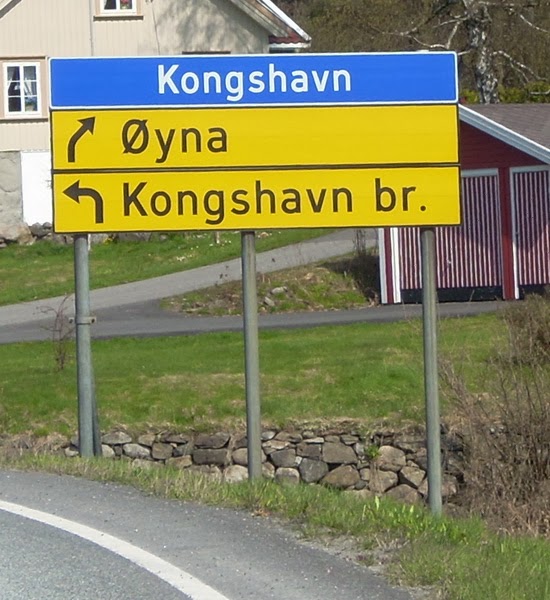
Suecia - Tratex
Anteriormente conocida como GePos, la Tratex es una Sans Serif geométrica diseñada por Kåge Gustafsson con la finalidad de conseguir la máxima legibilidad posible.
Holanda - ANWB/RWS
Desde 1960 en Holanda se usaba para la señalización del tráfico la versión ANWB-Ee, pero en 1997 se contrató a Gerard Unger para que diseñara la versión ANWB-Uu.
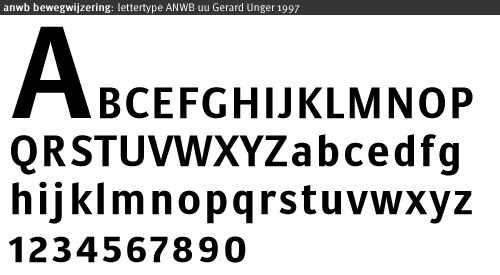
Eslovaquia - Universal Grotesk
Esta tipografía diseñada en 1951 es la elegida ( y mas en concreto las versión Bold y Condensed) en Eslovaquia para ser utilizada en todas las señales de tráfico del país.
Oye! Excelente post/artículo.. no es usual encontrar este tipo de información, gracias!
ResponderEliminarNo me gustan mucho las neo grotescas con esos trazos cerrados aunque me parece que no generan riesgo de similitud como a mi me parece en la legibilidad (por ejemplo la a de la de Suecia no me parece acertada, ahi seria una letra geométrica). Por ello simpatizo con Frutiger. La «transport» me ha gustado, ¿carretera convencional, la llamamos aqui? viva Epañiaaa jejeje. La de Singapur es curioso! además el cartel no se si será por ser bold no parece rotis. El cartel de la francesa se ven anchas, es agradable... esta muy chulo el artículo y original, un detalle tantos ejemplos. Merci!
Una cosa solamente, ya que dices que la Frutiger no se trata de una letra geométrica, no esta bien decir que ninguna de las cosas ya que se puede clasificar en ambos grupos (humanista o geométrica). Yo diría que no es estrictamente geométrica pero tampoco es estrictamente humanista.
EliminarEsta información no está completa. En España se usan dos fuentes diferentes (http://es.wikipedia.org/wiki/Se%C3%B1ales_de_Tr%C3%A1fico_Verticales_de_Espa%C3%B1a#Tipograf.C3.ADa). La "Autopista" (derivada de la FHWA Series E, http://es.wikipedia.org/wiki/FHWA_Series) y la "Carretera convencional" (o Traffic Type Spain D, derivada de la Transport británica http://en.wikipedia.org/wiki/Transport_typeface). Es fácil distinguirlas ya que sus eles son muy diferentes.
ResponderEliminartardé un poco en ver este interesante artículo. La ARIAL , si bien es cierto, es una tipografía cavernícola, cumple su misión; FUNCIONALIDAD. Yo me cansé de ella, pero no la podemos reprochar. No me convence el ejemplo en Francia... la fuente no es muy mala, pero sí lo es la distribución de ella en cartel. Soy de Paraguay y aquí ocurre lo mismo que en varios países latinos...varias tipografías en diferentes rutas, creo que eso ocurre porque no existe una regla o ley reglamentadora que controle UN tipo de fuente que debe ser para toda la cartelería